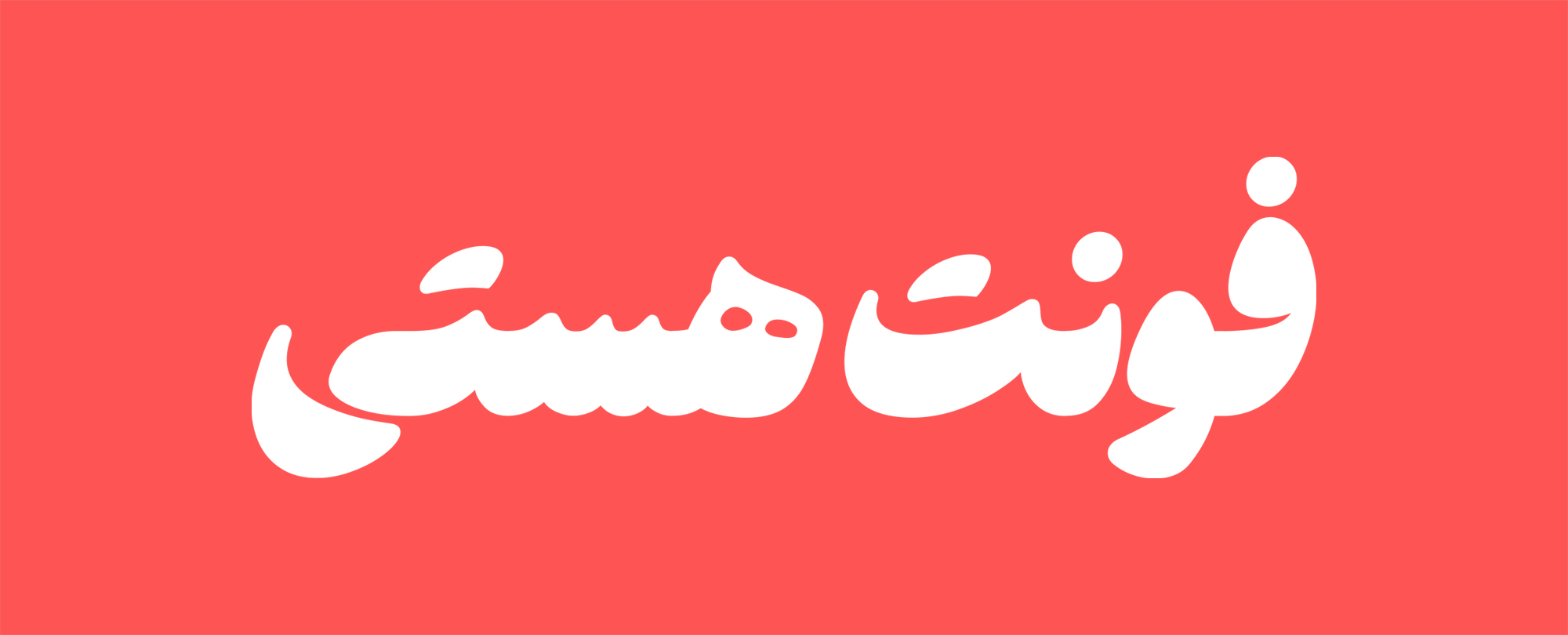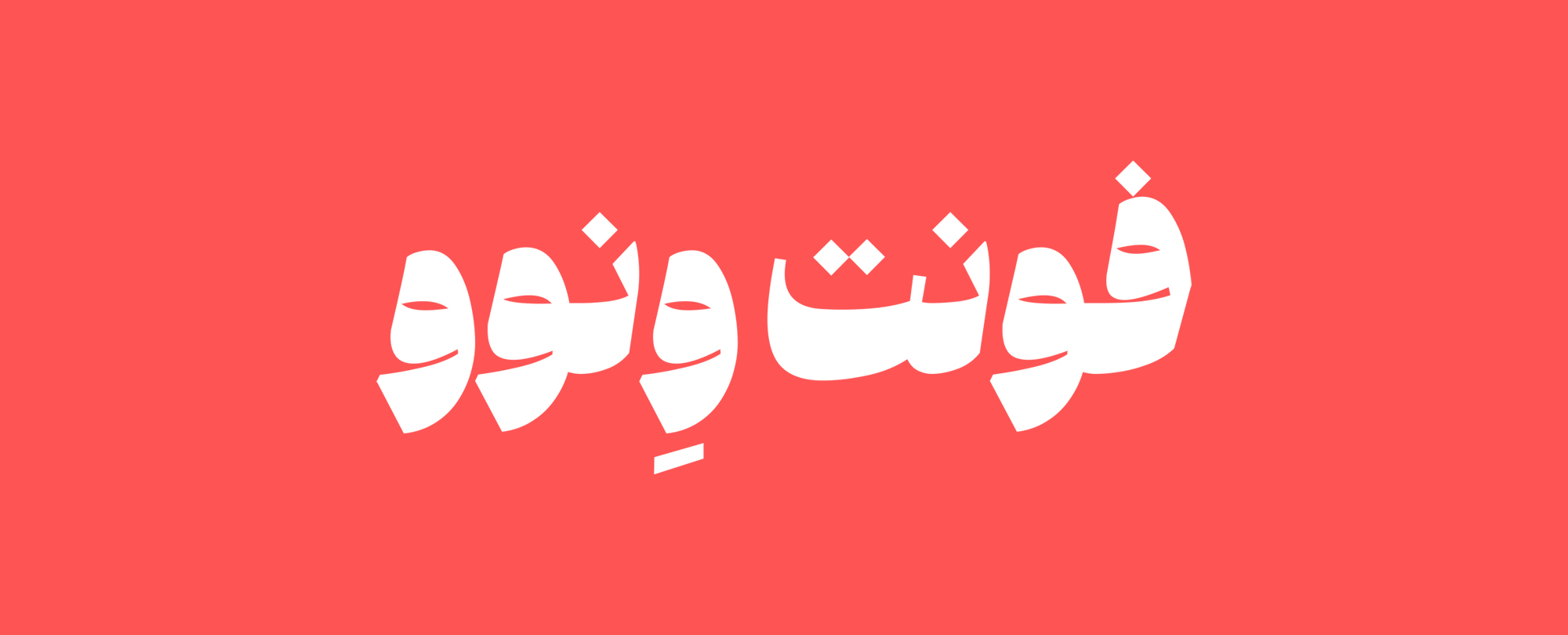
"فونت ونوو" از دسته نسخ، اما مدرن و معاصر است. این فونت با توجه به ویژگیهای منحصر به فردی که دارد، قابلیت استفاده در کاربردهای مختلف را داراست. کنتراست ضخامت، وزنهای متنوع و امکاناتی که "ونوو" در اختیار شما قرار میدهد، میتواند جلوه ویژه و متفاوتی از نوشتار را به نمایش بگذارد و توجه مخاطب را جلب کند.
فونت ونوو را میتوانید در کاربردهایی مانند تیترهای مطبوعاتی، انواع بستهبندی، گرافیک محیطی، وب و محتواهای رسانههای اجتماعی استفاده کنید و از تجربه کردن یک فونت جدید لذت ببرید.
فونت ادامه نتیجهی تلاشهای من برای مطالعهی جزییات در هندسهی خوشنویسی ایرانی در کلاس استاد دامون خانجانزاده است. با تبدیل اتودهایم به فرمهای سنگین، به مرور این فونت را با هدف استفاده در تیترهای تککلمهای و متنهای کوتاه پیش برده و آن را کامل کردم.
فونت هستی حاصل آمیختن نسخ با نستعلیق است. نسخ نسخهٔ کاربردی از خط عربی و نستعلیق اوج زیبایی خط فارسی است. فونت هستی در میانهی کاربرد و زیبایی، سعی کرده است حروف سیال نستعلیق را بر کرسی بنشاند و مانند خط نسخ آرام کند.
فونت هستی شبیه هیچکدام از فونتهای پیش از خود نیست اما آشناست و به آسانی ارتباط برقرار میکند. شباهتی که با نستعلیق دارد کلید برقراری این ارتباط است.
فونت کوک از دستهی فونتهای مناسب متن با ساختار هندسی است. اگرچه اسکلت کلی فونت کوک مشابه دیگر فونتهای هندسی فارسی است اما ظرافتهای اجرا معاصر است. برشها قلم کمی زاویه دارد. بعضی مفصلها دارای شکست و زاویه تند است. و خمیدگیهای خارج از قاعده در برخی حروف دیده میشود. همه این ظرافتها کمک میکند بافت بهتری در متن ریز به دست آید و روان خوانی افزایش یابد.
فونت کوک بیشتر مناسب موضوعات معاصر تبلیغاتی، طراحی رابط کاربری و محتوای شبکههای اجتماعی است. فونت کوک مناسب متن است اما شاید برای خواندن متنها خیلی بلند ایدآل نباشد.
ابَر چند شخصیت دارد. نوجوانی بهروز و با ادب است، واضح و صریح حرفش را میزند. جوان است و مدیر کسبوکاری آیندهدار، با ملاحظه اما قاطع صحبت میکند. جاافتاده است و با تجربه، گرم و شیرین سخن میگوید.
ابَر جاهطلب است، پرطمطراق است، جسارت دارد، برای زیبایی ارزش قائل است.
ابَر منعطف است. با آن میتوانید از رمزارز بگویید، دربارهی آشپزی حرف بزنید یا از ادبیات کهن یاد کنید. میتوانید در کتاب داستان، پوستر فیلم، منوی کافه، بیلبورد تبلیغاتی موبایل یا وبسایت بانک با آن بنویسید.